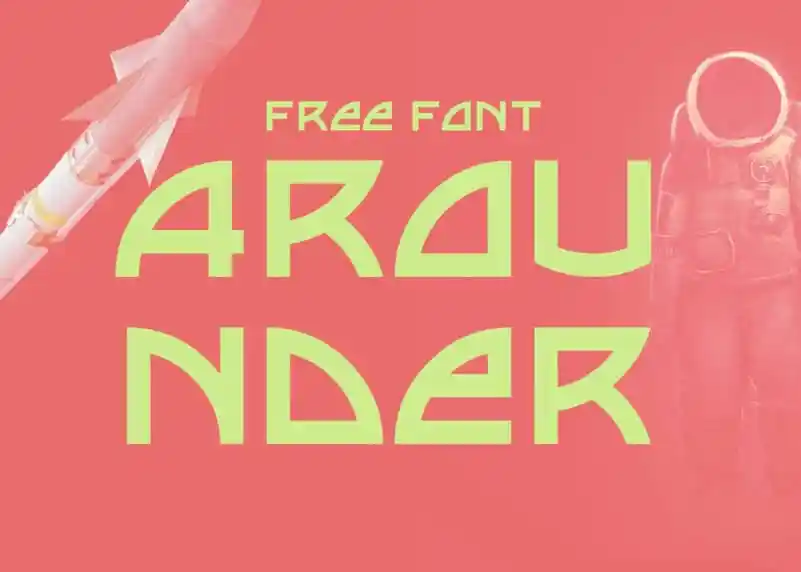
Arounder Display Font – Fonte Grátis
Arounder Display Font
Arounder Display Font é uma fonte expansiva futurista à disposição gratuitamente, criada por Maxim Raikov. Essa fonte oferece um equilíbrio harmonioso entre modernidade e simplicidade, ideal para designs que buscam agregar um toque único e inovador. Seja em aplicações digitais ou impressão, Arounder Display traz uma abordagem futurista, mantendo sempre o equilíbrio visual essencialmente moderno. Se você está procurando por uma fonte que não só destacará seu design, mas também adiciona um elemento de aventura e inovação ao seu projeto, esta é a fonte perfeita para você. Esta fonte foi desenvolvida pelos mestres da 99designs, onde designers de todo o mundo compartilham suas habilidades criativas. Arounder Display oferece um conjunto vasto de opções, que vão desde as letras mais simples até elementos mais elaborados, permitindo uma ampla gama de possibilidades para seus projetos visuais. Com Arounder Display, você pode criar designs contemporâneos e modernos sem sacrificar a estética clássica dos padrões futuristas. Seja no design editorial, gráficos em redes sociais ou logotipos empresariais, essa fonte é uma escolha inteligente para aqueles que prezam por um visual moderno e inovador.